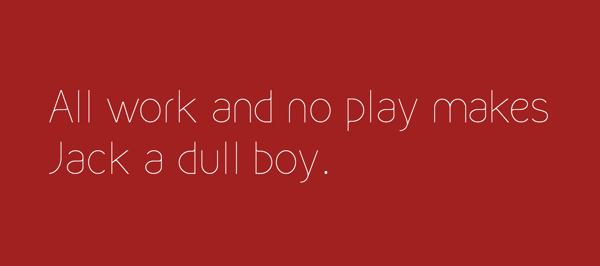
Las segunda tipografía del día que os traigo es otra tipografía sin serifa del mismo autor que la anterior, os dejo los links abajo. Espero que os guste y recordad que los like y los follow ayudan mucho así que visitadnos en Twitter y Facebook. También nos podéis encontrar en Flipboard buscando nuestra revista El Arquitecto de Ilusiones.